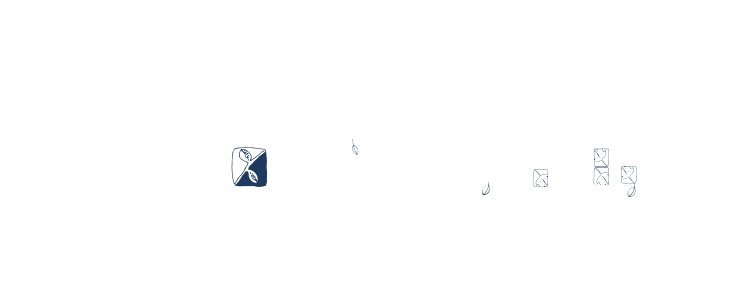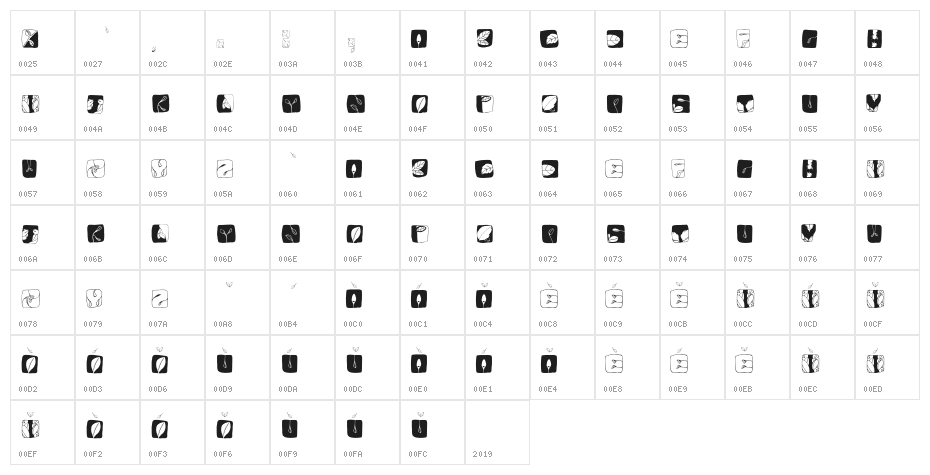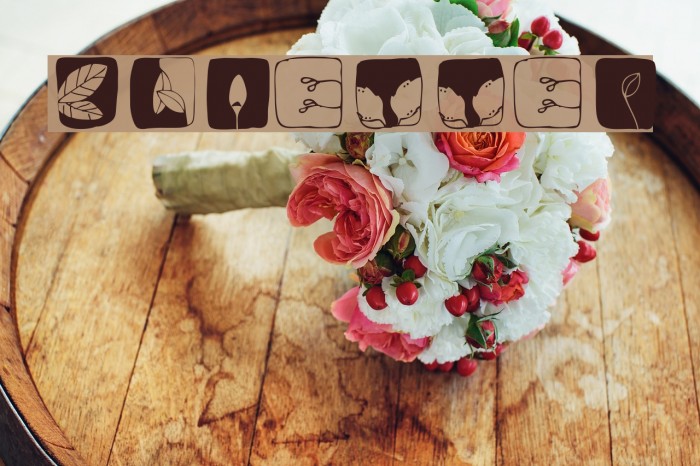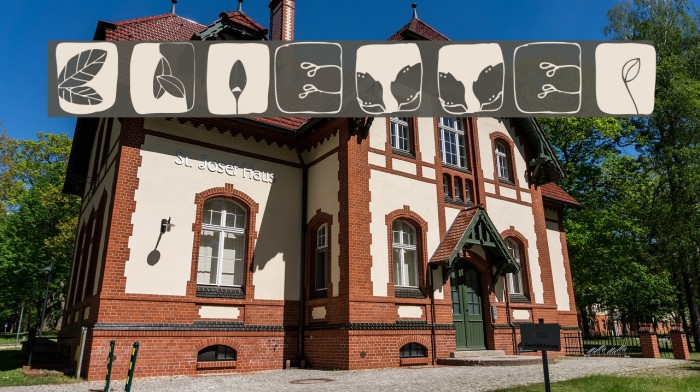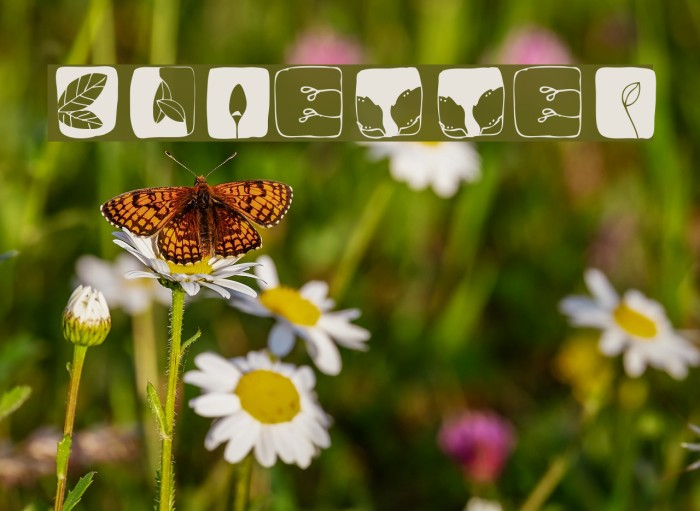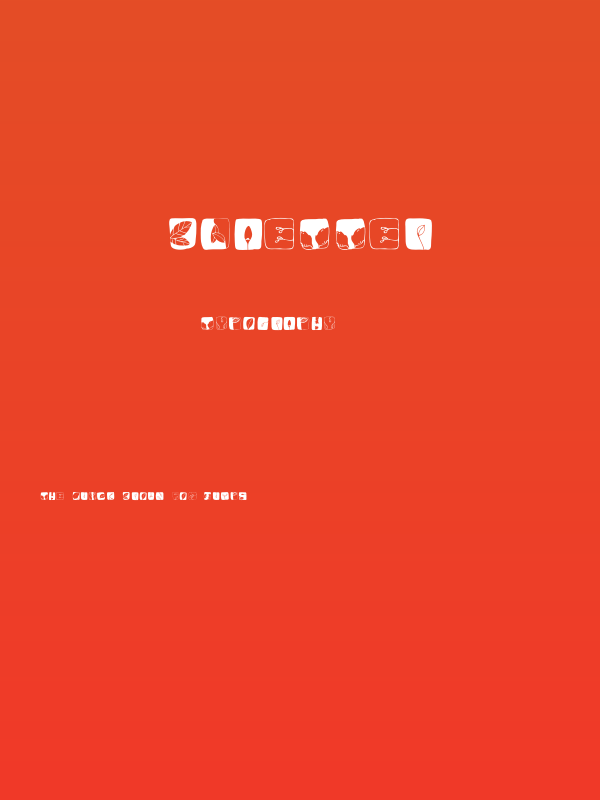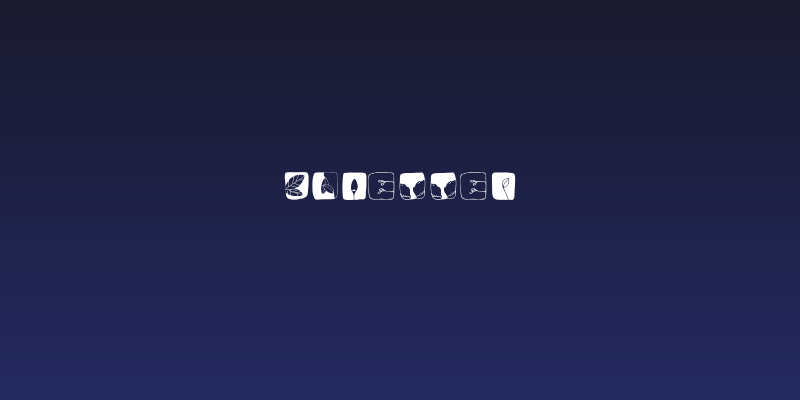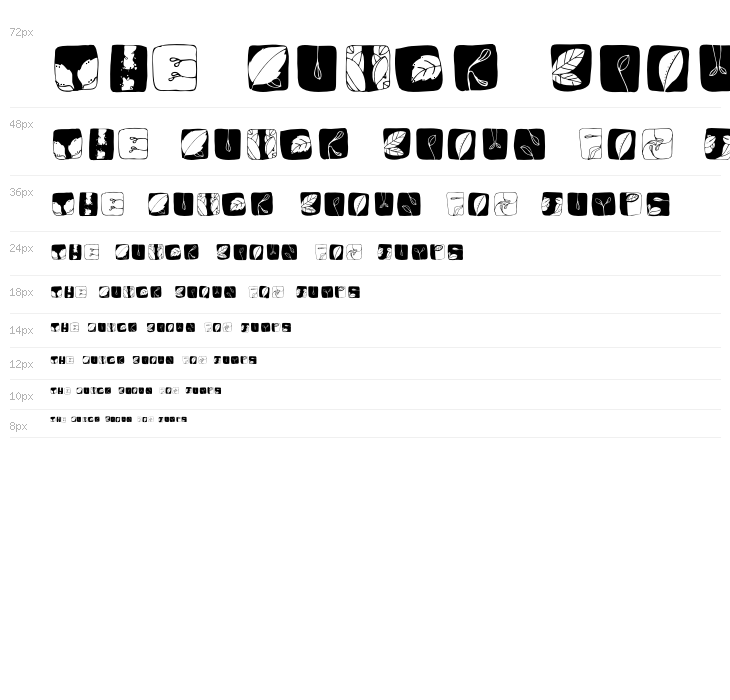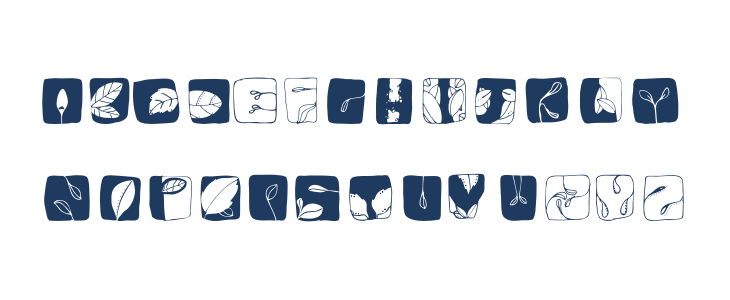
blaetter Font
| Caso d'uso | Logos, Posters, Artistic Designs |
| Progetti proposti | Ideal for eco-friendly branding, nature-themed posters, environmental campaigns, and artistic projects. |